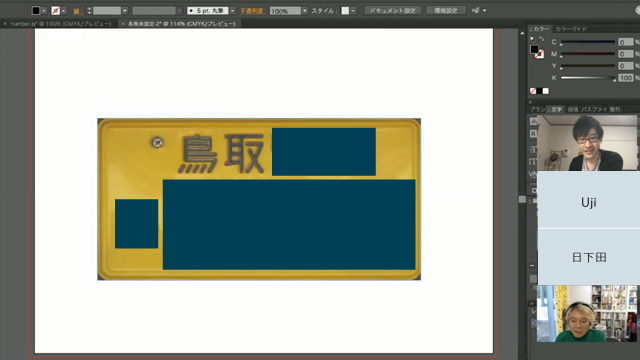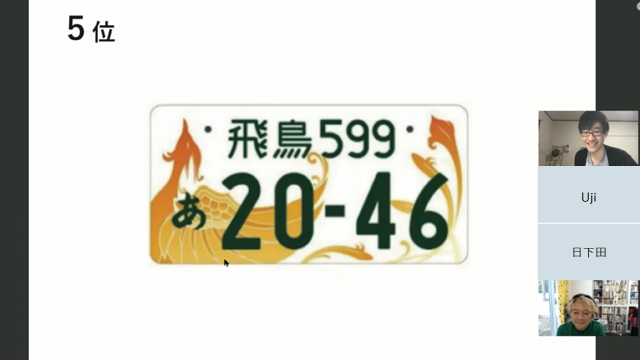
愛でよう、ナンバープレートの地名
さて、冒頭で述べた新たなご当地ナンバー17種がご覧のとおり。
その地域らしさを詰め込んだ背景デザインも気になるが、今回の主役は文字。この記事を通して彼らの魅力が少しでも伝わればいいな、というのが今回の記事のテーマである。
「ナンバープレートの地名の文字を愛でる会」、お声がけしたメンバーは以下の4名だ。
そしてデイリーポータルZからは以下の2名でお送りします。
地名フォントのかわいさは、「おしゃれ寄り」と「不思議寄り」のふたつある
さて、現在交付されているナンバープレートは全133種。
参加者には事前に全ナンバープレートをお見せして好きなものを5つ選んでいただいた。泣く泣く候補から外したものも多く、それぞれ何を選んだのかとてもワクワクしている。
まずは筆者から。
5位:飛鳥
北向:じゃあ発表はじめますね、まずは「飛鳥」です。
全員:あー!
日下田:このナンバープレート欲しいですよね、飛鳥ナンバーって言いたい。
北向:やっぱり「鳥」の下の「灬」ですよね、この斜めの角度の揃い方…!名前もデザインもわかりやすく格好いい…
5位はつい先日発表された新しいナンバーから選出した奈良の「飛鳥」。
選定ポイントは何より「鳥」のスタイリッシュさなのだけど、実はこの飛鳥より人気の「鳥」を使った地名がこのあと出てくることになる。
4位:山形
北向:4位はこちら、山形。
日下田:あー山形!そうですよね!
北向:何よりこの「形」の「彡」が「三」になっているところが、もうかわいくて。
ナンバープレート全種を並べても、ここまで大胆に斜めの画(かく)を水平にしている文字はなかった。なんでそんな独自路線を走るんだ山形。
地名を眺めていると、「かわいさ」の種類が大きく二つに分かれることに気づく。
ひとつが先の飛鳥みたいな「デザインしてやるぞ!」という洗練されたかわいさ。一方で他ではあまり見かけないような不思議なバランスのものもあって、それもまた魅力なのだ。
そういった後者の「不思議かわいい」部門にあげたいのがこの山形である。のちに発表する林さんも、わりとこの不思議かわいい文字が気になる派だった。
3位:練馬
北向:3位はかぶらないんじゃないかなと思ってるんですけど、練馬…
全員:あっ。
えっ、133種あって全員かぶるとかあるのか!じゃあ、ということで練馬の話は最後尾のUjiさんの発表時に回すことにした。
この”練馬全員かぶり”から、テレビ会議特有の出だしの緊張感がほどけた感じがした。地名を愛でる会のグルーヴが芽吹いた瞬間だ。
2位:奈良
2位に挙げたのが奈良。先ほどの飛鳥といい、奈良県勢がつよい。
日下田:かわいい〜。
北向:見るからにかわいいですよね、この「奈」。
Uji:どこかアイドルっぽさを感じますね。
北向:アイドルっぽさ!
Uji:華やかさというか、「大」と下部分と、花が開いているような…
Ujiさんの”アイドルっぽさ”という表現が印象的だ。そうか、奈良は地名界のアイドルだったんだ。
1位:滋賀
全員:あ〜〜滋賀〜〜。
滋賀は自分が「ナンバープレートの文字かわいいな」と思ったきっかけの、思い入れのある地名だ。これはもう、誰が見てもかわいいのではないだろうか、推しの地名である。
林:「滋」、ヒエログラフみたいですよね。
北向:あ〜、祈ってる人みたいですね。
Uji:何かをしゃべっているみたい。
北向:屋根がある場所で。
日下田:「祈り」の文字だったんだ…
北向:「賀」も。下の払いの出てる位置が革命ですよね。
日下田:初めて見たときにこんなことしていいんだ、って思いました。
Uji:3Dプリントにしたら安定感ありそうですね。
北向:あー、「滋賀を置くならこう」って感じだ。
文字ひとつとってもみんな注目しているところが違う。これは楽しいぞ、自分の知らない文字の良さがいろんな角度からにじみ出てくるのだ。
キーワードは”墨だまり”
2人目は日下田さん。
文字集めが趣味とのことでお声がけしたのだけど、会がはじまってからのテンションの高まりと笑顔から本当に文字が好きなのだな〜という熱が伝わってくる。どんな地名が出てくるのだろう。
5位:江東・香川
日下田:2つあって、「江東」と「香川」なんですけど…
Uji:あ〜〜かわいい(声が漏れるように)
日下田:ナンバープレートの文字を見ると、どれも結構正方形にしたがっている(横に広い)印象なんですね。
そのなかでこのふたつは東の田、香川の日の部分が引き締まっていて、現代的だな〜と感じました。
Uji:(おおきく頷く)
林:へぇー、第2世代ですね。
日下田:今ふところの小さい字が流行っているイメージなんですけど、この「香川」は昔からある地名のフォントなのに洗練されているのがおもしろいなあと。
林:そういう目線があるんだな〜。
林さんと同じく、そういう目線があるんだな〜!と思いながらふんふん話を聞いていた。普段からフォントを見ている方々の視点はとても新鮮で興味深い。
実はもうひとつあった5位が「練馬」。飛ばします。
4位:青森
北向:青森!わかる〜。
日下田:月のデカさがいい…。さっきの「香川」と逆で、おおらかな感じ。
日下田さん曰く、ナンバープレートは”墨だまり”っぽさがチャーミング、とのこと。
墨だまりとは、”線が重なる箇所に溜まったインク”の部分のことだそうだ。写植特有の雰囲気を再現し、やさしい印象になる。すごい、今日勉強になるな…!
ナンバープレートの文字は総じて丸みを帯びている。これは推測だけど、プレートをプレスする際に、文字に角があるとうまく処理できないのではないだろうか。とのこと。
なにせこのフォント、統一されたものでもなく、どこの会社が作っているかも非公開とのことで詳細がつかめないのだ。我々にわかることはただひとつ、この文字がいい感じだ、ということ。さあさご両人、深いことは考えず引き続き目の前のいい感じの文字を愛でるぞ。
3位:岡山
3位は「”岡”がつく地名はたぶん5つあったんですけど、これが一番顔に見える」との理由で岡山。
2位:岩手
日下田:2位は岩手。もうかわいいでしょう、っていう。
日下田:岩手の岩の、「石」の部分ですよね、かわいい。
林:3秒見るともう岩に見えなくなりますよね。気づかなかったけどこんな形してたんだ。
北向:上の山をとっちゃうともう「石」には見えないですね、すごいギリギリのバランス…
日下田:岩手のナンバーはじめて見たんですけど、こんなのあったんだって。
確かに、東京近辺で暮らしているとなかなか岩手ナンバーの車を見かけない。今まで知らなかったかわいい地名っていっぱいあったのだ。もったいないことをしていたな。
1位:鳥取
日下田:1位は鳥取で。
林・Uji:あ…(二人とも鳥取をランクインさせていた)
北向:かぶりのため息が。
日下田:みんな…!
日下田:「取」の1画目、そんな伸ばしちゃうんだって。鳥も4つ点が揃っちゃうんだ…って。
Uji:「取」、背負い投げしてるような感じに見えますね。
日下田:すごい動的ですよね。「耳」の左下もかなり隙間があいてる。右に伸びる1画目を短くして、「又」を上あげたら普通のバランスなんですけど…
そっか、そう言われると右へ回転する動きが見えてくるようだ。不思議度が一番高かったとのことで、他をおさえ「鳥取」が堂々1位にランクイン。
日下田さんのフォントのトレンドなどを交えた解説のおかげで、文字の新しい見方が拓けた気がした。今まで文字を裸眼で見ていたところに眼鏡をかけさせてくれたような感じだ。
ロゴっぽさ、そして進化の過程っぽさを感じる文字たち
3番手は編集長の林さん。やっぱり5位は「練馬」とのことで4位からスタート。
4位:佐世保
林:4位は長崎の佐世保です。
北向:わー、佐世保!(頷く)
林:「保」の右下、カタカナの「ホ」ですよね。普通くっつけるのに気になって。ナンバープレートの文字って、漢字ができる成り立ちの途中みたいなんですよね。
言われてみると、多少簡略化されたその文字たちは、文字の進化の過程のようにも見えてくる。象形文字から段々と漢字になるような、漢字からひらがなに変わるような。その一種の幼さがかわいさの要因なのかもしれない。
3位:鳥取
3位は人気の鳥取。
林:鶏肉屋っぽくていいんですよ。ロゴっぽさがある。
日下田:あ〜、Tシャツに「鳥」だけ1文字入れてもかわいいですね。
さすがTシャツを数多く作っている日下田さんの発想だ。鳥Tシャツ、ちょっとほしいな。
2位:和歌山
林:2位は和歌山です。
日下田:へ〜!
北向:和歌山!ノーマークでしたね
林:和歌山、よくできてなくないですか?
全員:笑
林:「可」の「口」部分がやたら線が細くなっちゃってるのが。
日下田:確かに!フォントって、「線の太さが違うのに、均一に見える」ように調整してるんですけど、これ、明らかに口が細いですよね。
北向:和の「禾」も変ですね。
林:木が三角ですよね。
北向:水かきみたいになってる…
林:かわいい。
林さんが「かわいい、人間らしい」とぽつりとつぶやく。なるほどなあ、隙のある感じが確かに人を惹きつける、ぶさかわ文字である。和歌山なあ。
1位:和泉
林:1位は和泉です。こう、泉感があるんですよね、ファウンテンみたいな。
林:泉がほぼ左右対称ですね。知らない百貨店のロゴみたいな。
Uji:印鑑っぽいですね。
日下田:かわいいですね〜。
林さんは全体を通して文字のアンバランスさを愛でていた。和歌山など完全にスルーしてしまっていたので目から鱗だ、見落としていたなー。
ナンバープレートは「作品」
ラストはUjiさん。ナンバープレートの一覧をおくった時点で「素敵な作品が多くて選ぶのがむずかしい」と、ナンバーを”作品”と呼んでいた。お声がけしてよかった〜と感じた瞬間である。
順位の優劣はない、とのことで好きな5つを選定いただいた。
1つめ:足立
Uji:まずは「足立」なんですが…
全員:あ〜!
我々のボルテージは常に最高潮、みんな文字を隈なく眺めようとPC画面に前のめりだ。
Uji:足立は何と言っても「足」の足元のこのカーブ。かわいいなぁと。
日下田:いやぁこれ、かわいいですよね〜。
Uji:カーブの部分、シンメトリーではないけどちょっと上にあげちゃうんですよね。
日下田:ニコッとしてる感じがします。
どこかコミカルな印象を受ける足立。「立」のかなりタテ幅いっぱい取っている感じもかわいい。
3つめ:練馬
2つめは人気の鳥取とのことで割愛して、3つめはこれまた大人気の練馬。
その辺りも地域差があるのだろうか、「横浜」の文字にも似たようなレトロおしゃれな空気を感じたのだ。歴史的な背景が文字から見えてくる…?
5つめ:福井
Uji:最後は福井です。
北向:そうそうそう、悩みました!
Uji:何と言ってもこの大きな「井」。
北向・日下田:おおきない!
Uji:もう少し小さくしても読めると思うんですけど、なんで広げたのか…。
日下田:しめすへんもかわいいですね。最後の点の位置が。
Uji:「ネ」が深く切り込んでるんですよね、かわいい。
四角い箇所がありながら、カーブが差し込まれるバランスが好き、とのこと。
「私はこの福と井のコンビが好きです。」とのUjiさんの言葉に一同がしみじみ頷いて、ナンバープレートの地名の文字を愛でる会はお開きとなった。
好きなモノの好きな部分を伝える、聞くことの楽しさよ
ここには収まりきらなかったけれど、「岡」と「宮」の多様さ、改定前の「愛媛」「大分」の異質さ、数字の不思議なバランスなど話は尽きなかった。自分のなかだけで「なんだかいいな」と思っていたものは、誰かと共有していくことで「どこがよいのか」がはっきりと見えてくるのだな、それはとても楽しいことなのだなと思った。